フォントで気持ちを伝える「DNP感情表現フォントシステム」を開発しました
大日本印刷株式会社は、テキストデータを自動解析する技術を活用し、文章の内容や感情に合わせて、最適なイメージのフォントを自動的に判別して表示する「DNP感情表現フォントシステム」(特許出願中)を開発しました。本システムは、文章中の言葉や絵文字の意味を解析し、その文章を12種類の感情・イメージに分類して、それに最適なフォントに変換して情報を表示することができます。
「DNP感情表現フォントシステム」デモンストレーション動画
【開発の背景】
近年、SNSや電子メールなどが日常的に利用されていますが、文字によるコミュニケーションは、声のトーンや表情が直接伝わる会話に比べ、意図や気持ちが伝わりにくく感じることがあります。そこで、感情をフォントで表現する「DNP感情表現フォントシステム」を開発しました。
当システムには、DNPが「秀英体」の開発で培った文字表現技術の他、印刷物で用いてきた多様なフォントやコンテンツによるコミュニケーションのノウハウを活かしています。
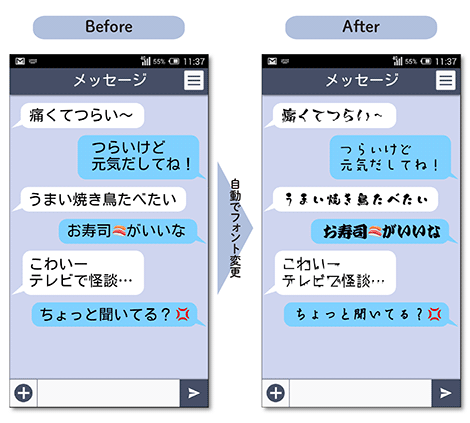
DNP感情表現フォントシステムの導入イメージ
【「DNP感情表現フォントシステム」の特長】
1.言葉・絵文字に応じてフォントを自動変換
文中の言葉や絵文字を解析し、それらが持つ感情やイメージから最適なフォントへ自動変換します。感情・イメージは、安らぎ、穏やか、楽しい、喜び、好き、哀れ、不安、恐怖、怒り、驚き、デジタル、ニュートラルの12種に分類しています。解析する単語や絵文字、感情やイメージ、変換するフォントの種類や数はカスタマイズも可能です。
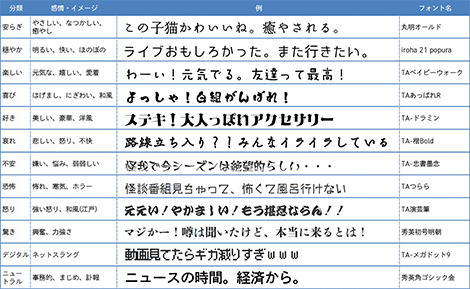
12種類の感情・イメージの分類と使用フォントの組み合わせ例
絵文字からの感情解析による最適フォントへの変換
2.入力するテキストのリアルタイムな分類が可能
テキストの入力時にリアルタイムで内容を解析し、順次フォントを自動判定しながら、文章全体で感情・イメージを伝えるフォントに変換します。また、利用者自身が自分の好みのフォントを選択する機能もあります。今後は、本システムで利用者のフォント選択結果(ログ)を収集して、さらなる判定精度の向上を図っていきます。
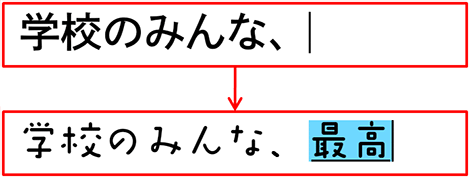
テキスト入力時のリアルタイムなフォント変換
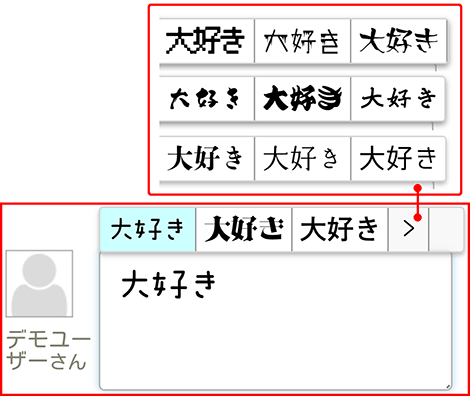
候補書体からの選択機能
今後は、当システムの導入先のニーズに応じた商品開発や、AI(人工知能)の精度アップを進めます。
SNSやチャットボット、デジタルサイネージなどさまざまなシーンで、フォントによる豊かなコミュニケーションの実現を目指していきます。
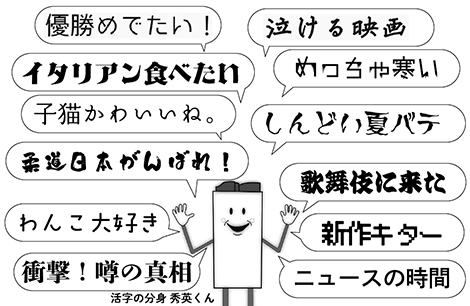
チャットボット(キャラクター)への活用イメージ
※「DNP感情表現フォントシステム」は、2006~2007年に慶應義塾大学・清木康(KIYOKI
Yasushi)研究室とDNPが共同で推進した「書体の感性データベース」研究を基礎概念として発展させ、DNPが2018年に開発したものです。
※当システムは、株式会社リアルタイプのウェブフォントエンジンと、砧書体制作所、スキルインフォメーションズ株式会社、大日本印刷株式会社のフォントを用いています。